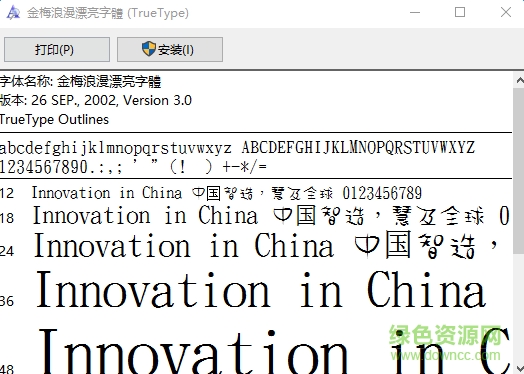
金梅浪漫漂亮字體是金梅字庫(kù)中很有個(gè)性的一款電腦字體,寫出來(lái)的字是很好看的,不拘一格,可以用在很多方面,只要大家喜歡,隨時(shí)都可以來(lái)綠色資源網(wǎng)下載使用。
這款字體不像普通的字體那樣呆板,它是很有活力的,而且用在藝術(shù)設(shè)計(jì)方面應(yīng)該會(huì)很不錯(cuò)的,大家可以下載試試看哦。